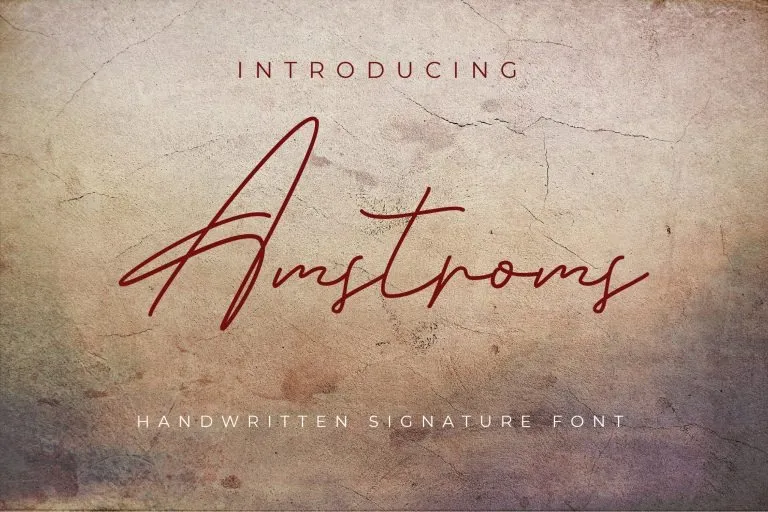
Amstroms Font – Download Grátis
A Amstroms Font é uma assinatura elegante e elaborada, perfeitamente adaptada para estilos de design personalizados. Com seu traço monoline, a Amstroms se destaca por sua inclinação pronunciada e suas letras com ligaturas para um caráter divertido. Ela apresenta também alternativas mais baixas para a escrita minúscula, o que resulta em uma mistura única de graça e elegância. Ideal para qualquer design exigindo personalidade, como cartões de convidados de casamento, cartões de agradecimento, cartazes de evento ou logotipos, a Amstroms é uma escolha versátil e encantadora. Sua natureza única e versátil torna-a perfeita para criar um toque especial em qualquer projeto visual.